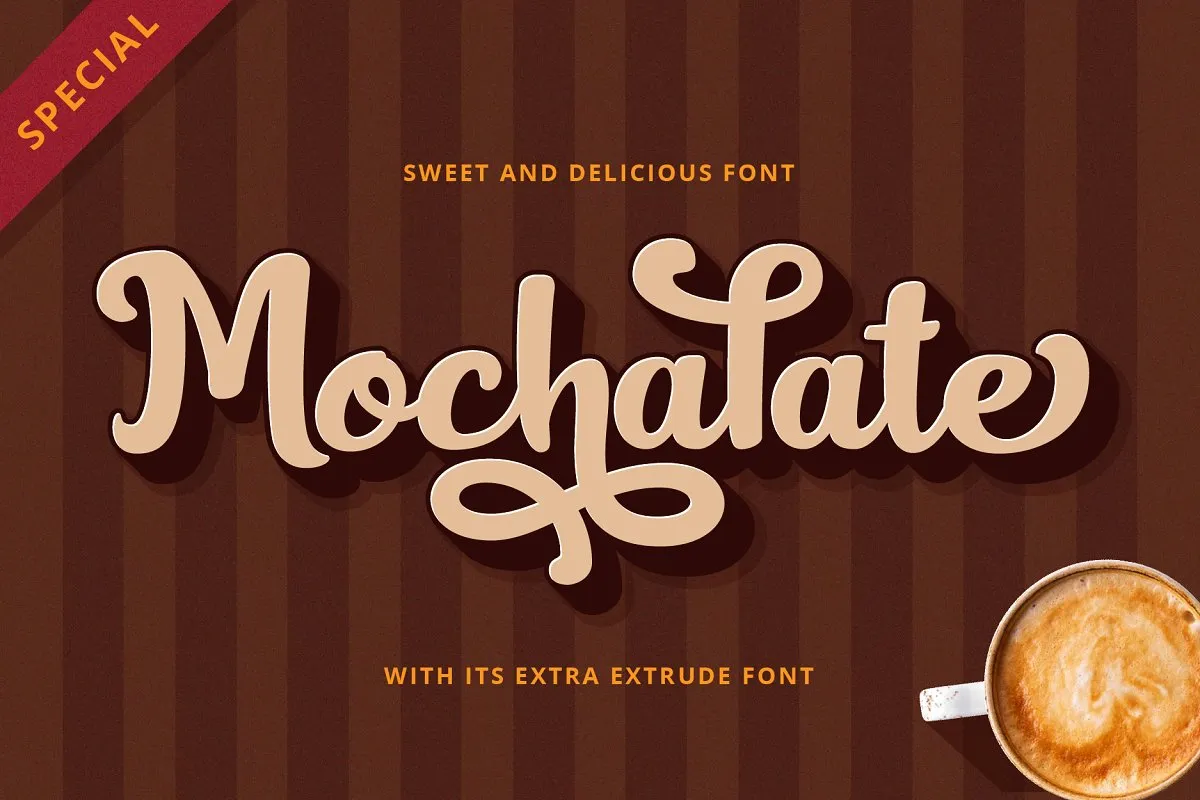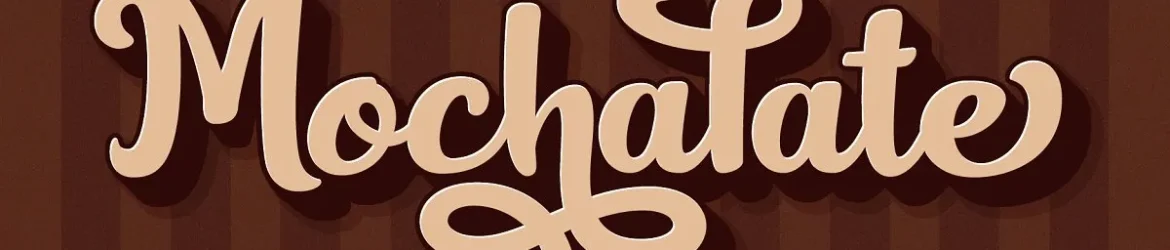
Esta fonte foi projetada a partir das escritas à mão e apresenta formas únicas de churrasco moderno. Ela tem um estilo de escrita natural, trazendo uma sensação tranquila aos seus designs. Introduzimos a fonte Mochalate Font. A Mochalate é um tipo bold, com sabor intenso e doce. Ela vem em versão sombreada extrudada única. Imagine como o mochacoffee, uma combinação perfeita de chocolate quente e café grande e espesso. É da mesma maneira que um delicioso bolo de chocolate saído do forno recentemente, com cheiro irresistível. Esta fonte é ótima para qualquer tipo de uso visual, desde embalagens, títulos, posters, headlines até logotipos.